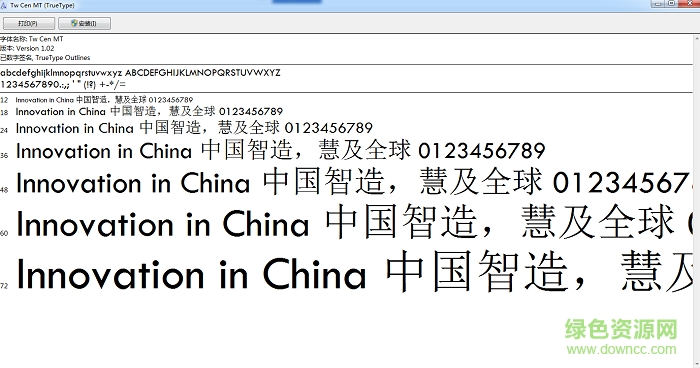
twcenmt-regular-普通體
tw cen mt regular字體是一款清晰易讀的英文字體,結(jié)構(gòu)嚴(yán)謹(jǐn),字面較大,具有明快的閱讀效果,一般用在文章的標(biāo)題、宣傳標(biāo)語(yǔ)、廣告海報(bào)上,需要的朋友快來(lái)下載吧!